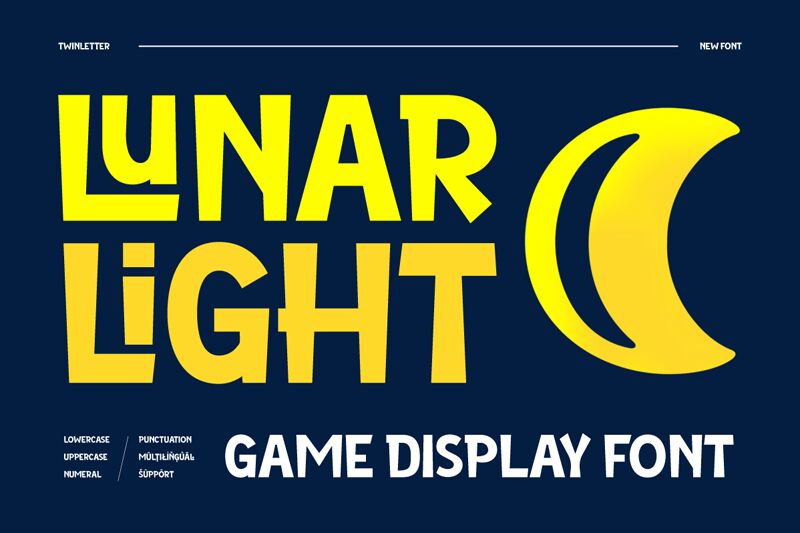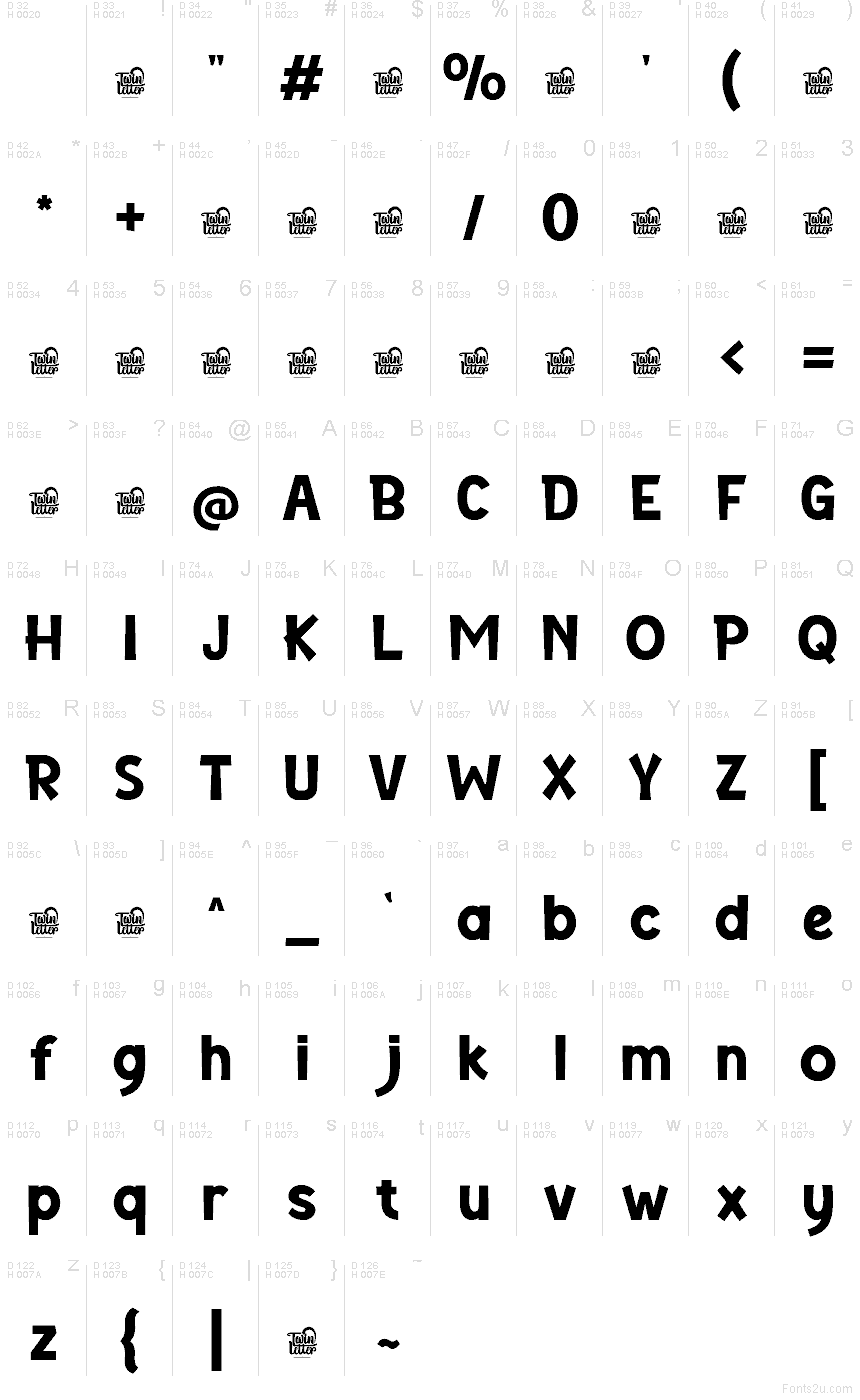
Lunar Light de Twinletter es una tipografía de rótulo de cómics gratuita, creada a partir de mayúsculas anchas e irregulares y ángulos de corte afilado. Las letras tienen un aspecto modelado a mano y ligeramente indócil.
El entretenimiento orientado a la juventud es su entorno más claro, especialmente los gráficos de videojuegos, los carteles musicales y el diseño de marca de ropa urbana. Sus siluetas densas y diagonales abruptas aportan un toque vivo y rebelde a dichos proyectos. En la mercancía, las letras pueden formar parte de la propia obra de arte, asemejándose a un emblema tallado a mano en lugar de a un texto tipográfico ordinario.